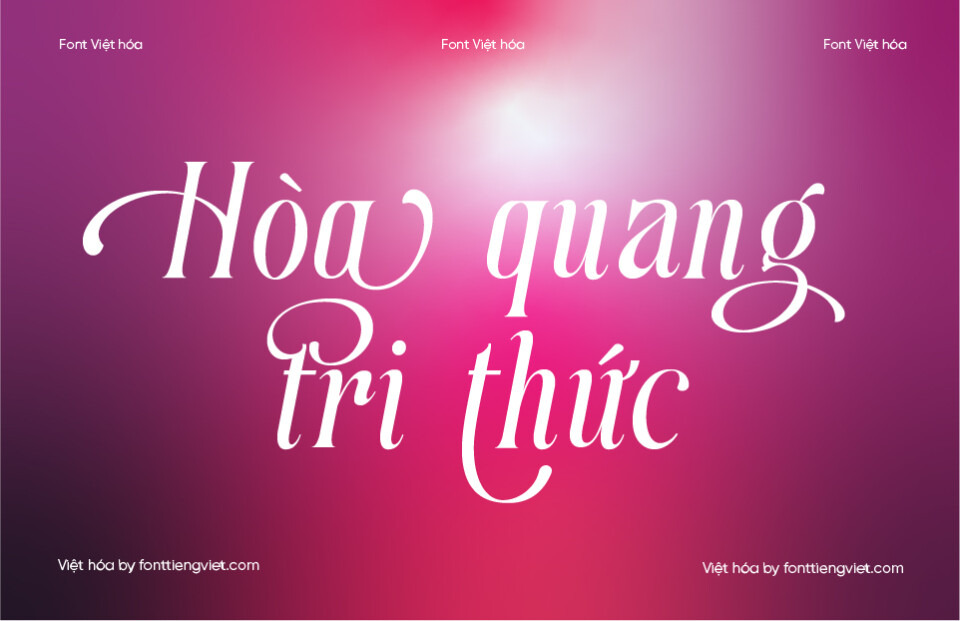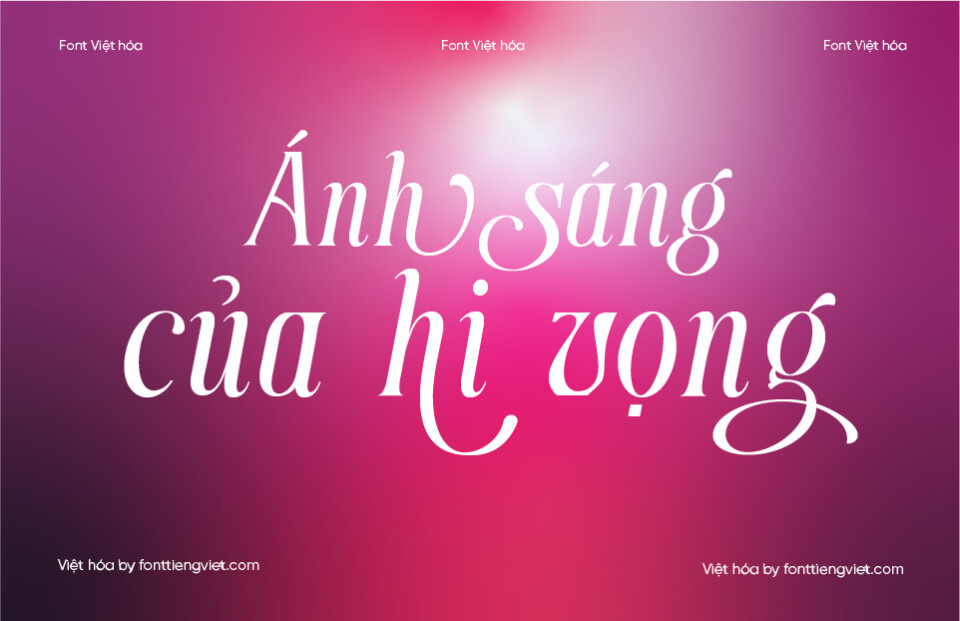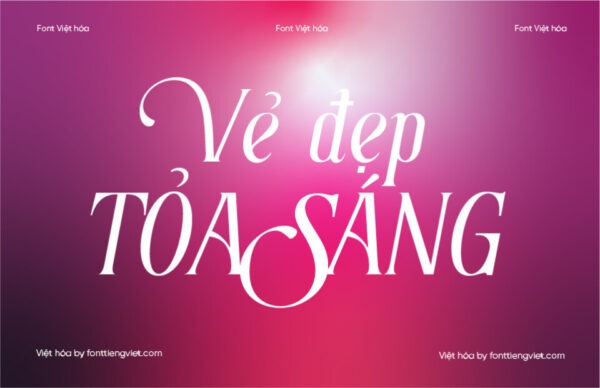
1FTV VIP Billing Lottre là font chữ có chân (serif) mang phong cách sang trọng, quý phái và đầy tinh tế, được Việt hóa chuẩn chỉnh giúp dễ dàng ứng dụng vào các thiết kế cao cấp. Font là lựa chọn lý tưởng cho những thương hiệu yêu cầu vẻ đẹp thanh lịch nhưng nổi bật.
Thanh lịch – Tinh tế – Đậm chất thẩm mỹ
Với từng đường nét uốn lượn, mềm mại nhưng không kém phần chắc chắn, Billing Lottre giúp nâng tầm các thiết kế thuộc lĩnh vực:
Spa, viện thẩm mỹ, làm đẹp
Thương hiệu trang sức, mỹ phẩm cao cấp
Poster sự kiện sang trọng, thiệp mời VIP
Website thương hiệu cá nhân hoặc showroom thời trang
Việt hóa hoàn chỉnh – Đáp ứng tốt tiếng Việt
Phiên bản Việt hóa của Billing Lottre hỗ trợ đầy đủ tiếng Việt, giữ được vẻ đẹp nguyên bản và bố cục hài hòa của từng ký tự. Thiết kế vừa nghệ thuật, vừa dễ đọc trong mọi định dạng hiển thị.
Đậm chất thương hiệu cao cấp
Font 1FTV VIP Billing Lottre là công cụ hoàn hảo để truyền tải sự đẳng cấp, tinh tế và chuyên nghiệp trong từng chi tiết, giúp thương hiệu của bạn tạo ấn tượng mạnh mẽ ngay từ cái nhìn đầu tiên.
Font Việt hóa 1FTV VIP Billing Lottre – Font chữ có chân sang trọng cho thiết kế spa, thẩm mỹ và trang sức